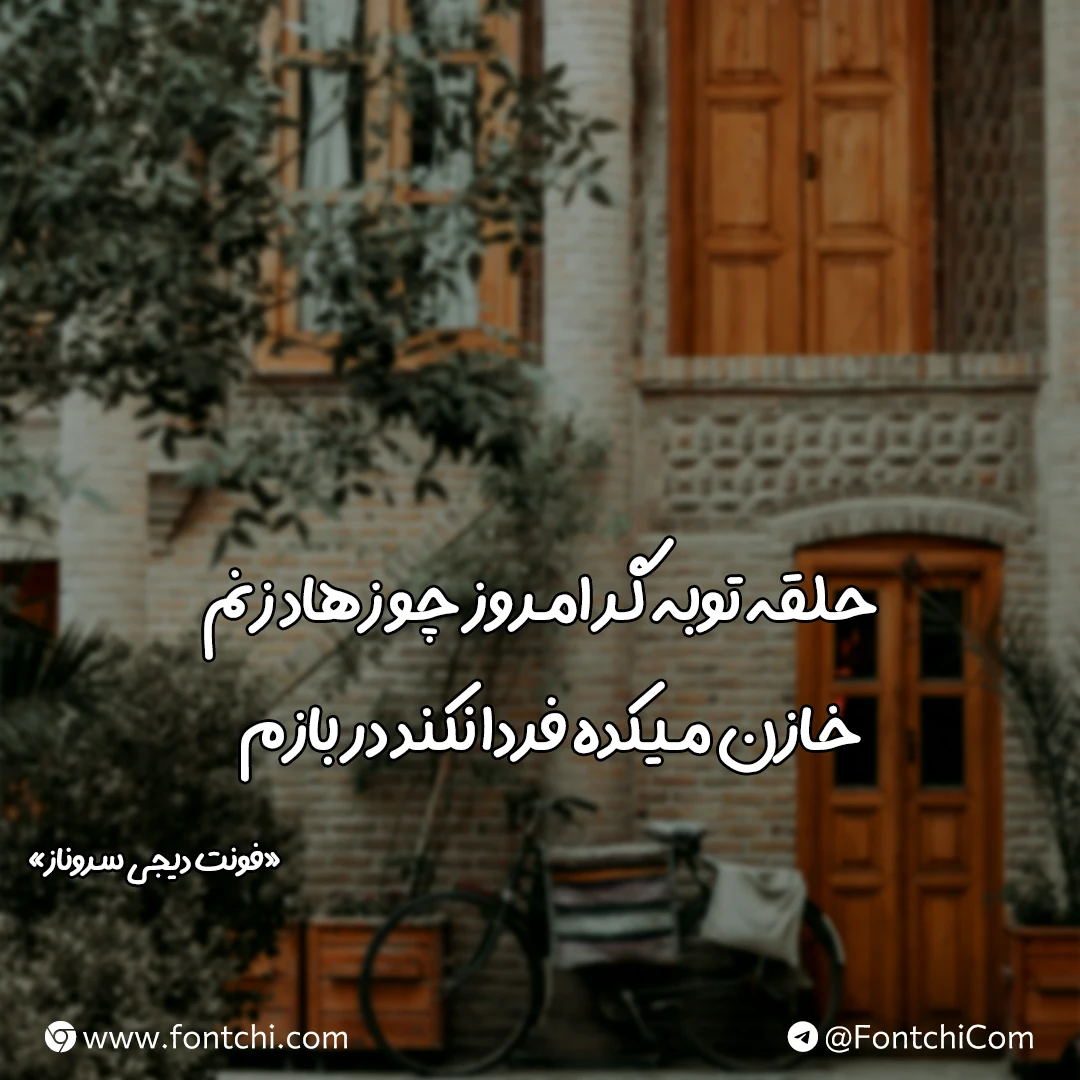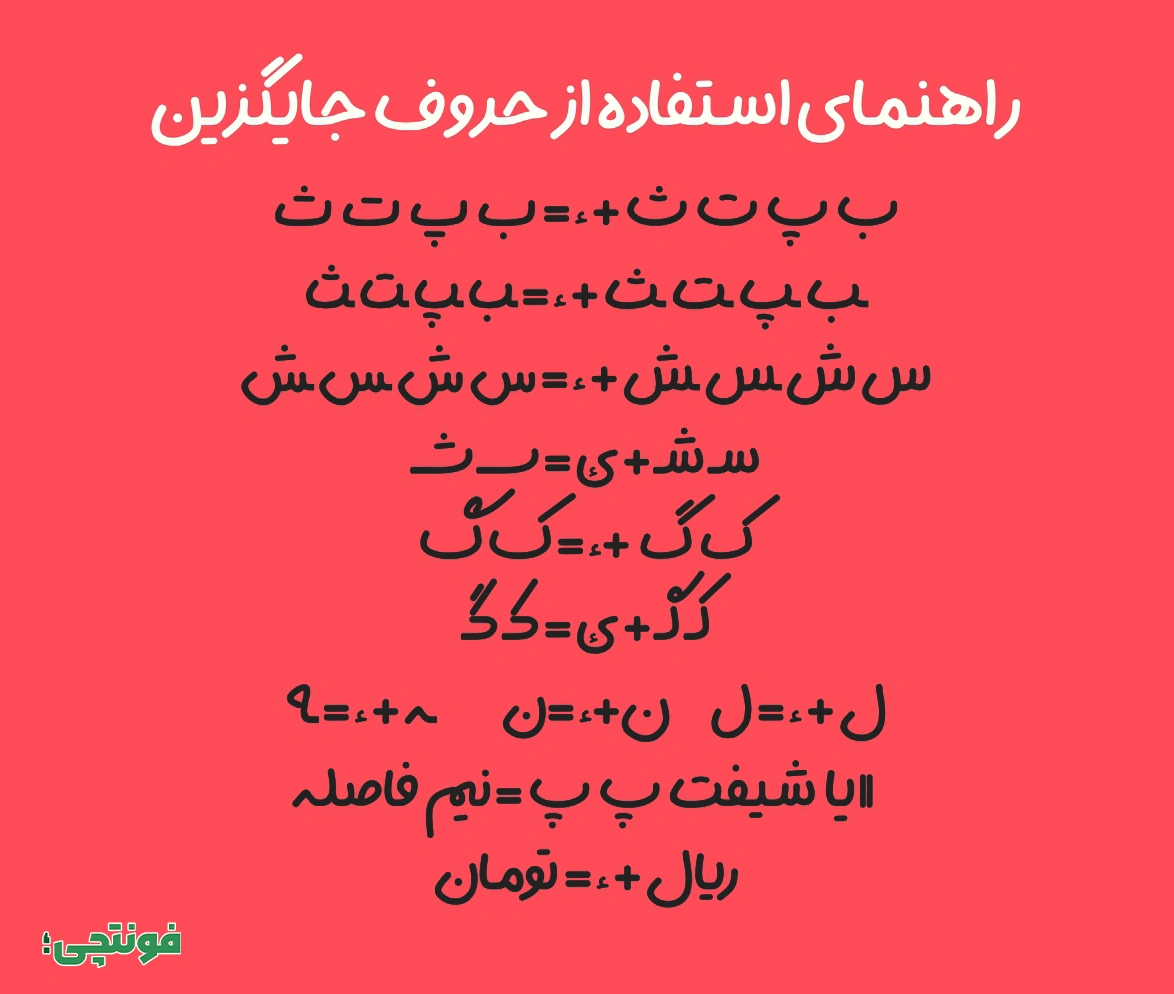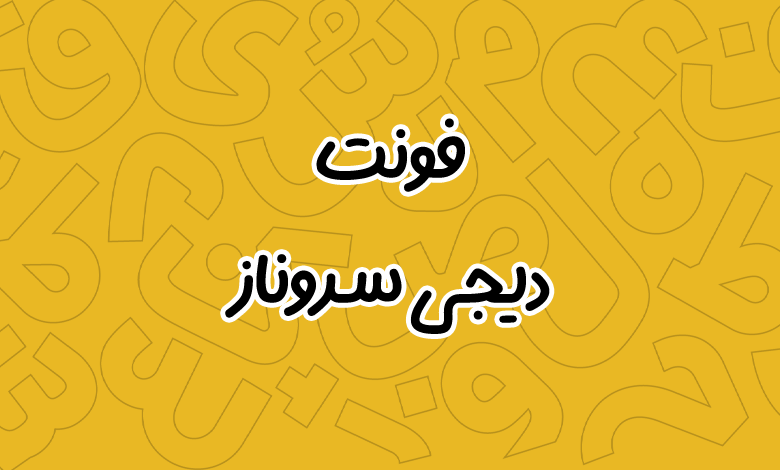
فونت دیجی سروناز (Digi Sarvenaz)
فونت دیجی سروناز یا سروناز (به انگلیسی: Digi Sarvenaz) از فونتهای دستنویس جذاب و کاربردی طراحیشده توسط مهدی برقگیر است که بهصورت رایگان در دسترس قرار گرفته است. با دانلود فونت دیجی سروناز میتوانید از این قلم در کارهایی که نیاز به صمیمیت و ارتباط با مخاطب ضروری است استفاده کنید.
این فونت جدید فارسی با استایل ضخیم و پاستیلی خود، سبک خاصی از فونتهای دستنویس را در خود جای داده است که آن را به گزینه مناسبی برای استفاده در پست شبکههای اجتماعی، عکس نوشتهها و صنعت چاپ همچون مجلات یا جلد کتاب تبدیل کرده است.
معرفی و دانلود فونت دیجی سروناز دستنویس (Digi Sarvenaz)
فونت دیجی سروناز بر اساس دستخط سمانه محمدی طراحی شده و با استایل ضخیم و پاستیلی خود، حس لطافت، شادابی و طراوت را به متون منتقل میکند. این فونت به دلیل شباهت زیاد به دستخط طبیعی، برای ایجاد حس صمیمیت و خلاقیت در طرحها بسیار مناسب است. کنتراست و ضخامت مناسب حروف، آن را به گزینهای ایدهآل برای متون تزئینی و فانتزی تبدیل کرده است.
پشتیبانی از زبانهای فارسی، انگلیسی، کوردی و عربی آن را به گزینهای چندمنظوره و مناسب برای مخاطبان با زبانهای مختلف تبدیل میکند. همچنین، پشتیبانی از اعداد فارسی، این فونت را برای استفاده در متون رسمی و غیررسمی که نیاز به نمایش اعداد بهصورت استاندارد فارسی دارند، کاربردیتر کرده است.
این فونت با کرنینگ متعادل فاصله بین حروف را بهصورت هوشمند تنظیم میکند و مانع از بههمریختگی در متون میشود. همچنین، اعرابگذاری حروف، امکان افزودن اعراب به متون را بهصورت دقیق و زیبا فراهم میکند؛ این ویژگی برای متون ادبی یا مذهبی بسیار کاربردی است.
فونت دیجی سروناز به دلیل استایل فانتزی و دستنویس خود، برای کاربردهای خلاقانه و تزئینی بسیار مناسب است. برخی از مهمترین کاربردهای آن عبارتاند از:
- استوری و پستهای اینستاگرام: به دلیل ظاهر جذاب و خوانا، برای طراحی استوریها، کاور پستها و عکسنوشتههای اینستاگرامی بسیار مناسب است. حس لطیف و عاشقانه آن، برای متون احساسی و دلنوشتهها ایدهآل است.
- تایپوگرافی خلاقانه: خلق تایپوگرافیهای خلاقانه و متفاوت در پروژههای گرافیکی به کمک حروف و ترکیبات جایگزین دست شما را بازتر میکند.
- طراحی محصولات چاپی: فونت سروناز برای طراحی ماگ، کارتپستال، کارت هدیه و تیشرتهای فانتزی گزینهای بسیار جذاب است.
- شعارهای تبلیغاتی: ضخامت و کنتراست مناسب این فونت، آن را برای شعارهای تبلیغاتی که نیاز به تأکید و جلب توجه دارند، مناسب میکند.
- محتوای چندرسانهای: این فونت در نرمافزارهای ویرایش ویدیو و تولید محتوای چندرسانهای، بهویژه برای متون کوتاه و تأثیرگذار، در برنامههایی مثل کپ کات و اینشات عملکرد خوبی دارد.
به دلیل استایل فانتزی و غیررسمی، استفاده از این فونت برای متون رسمی یا اسناد حرفهای توصیه نمیشود.
راهنمای حروف جایگزین فونت دیجی سروناز
فونت دیجی سروناز از حروف و کلمات جایگزین پشتیبانی میکند که بهطور خودکار یا با استفاده از کلیدهای ترکیبی فعال میشوند. این ویژگی به طراحان امکان میدهد تا تنوع بیشتری در چینش حروف ایجاد کنند و متون را خواناتر و زیباتر کنند.
جایگزینها بهگونهای طراحی شدهاند که از تداخل حروف جلوگیری کرده و خوانایی متن را افزایش میدهند. کافی است صفحه کلید شما روی زبان فارسی بوده و از ترکیبات بالا استفاده کنید. در برنامههایی مانند فتوشاپ میتوانید از طریق glyph panel نیز به این ترکیبات دسترسی داشته باشید.